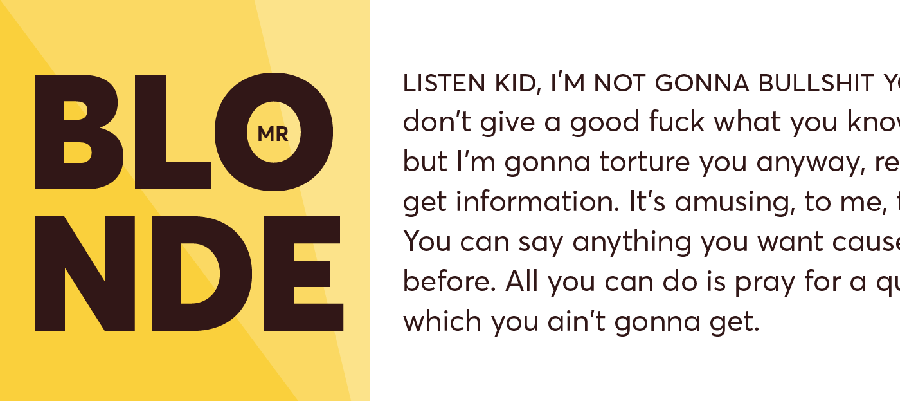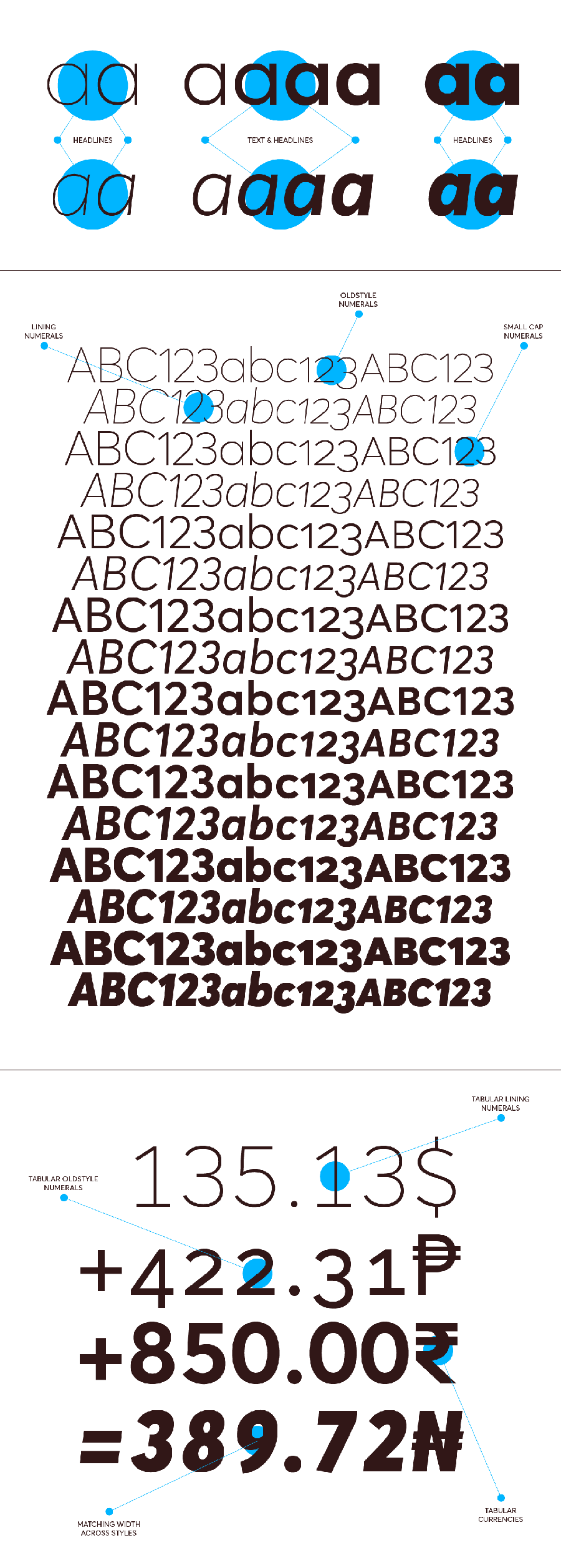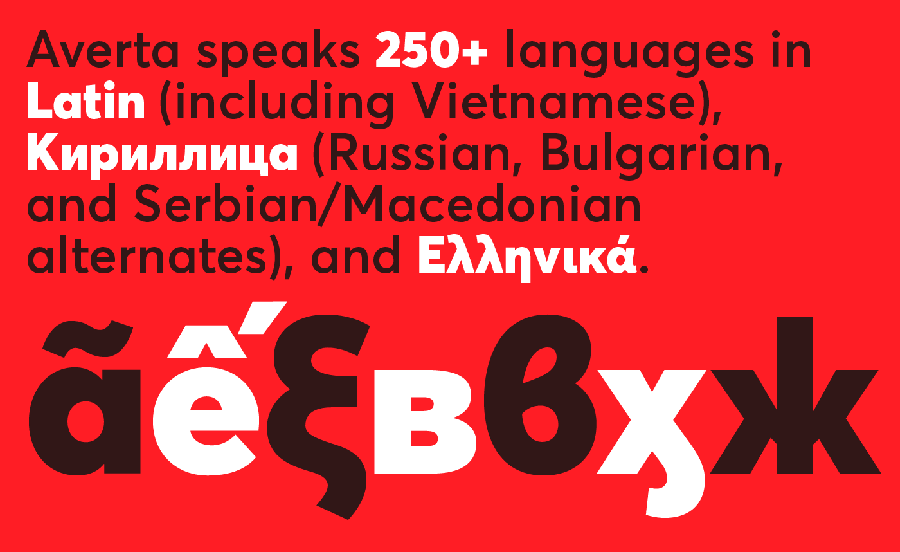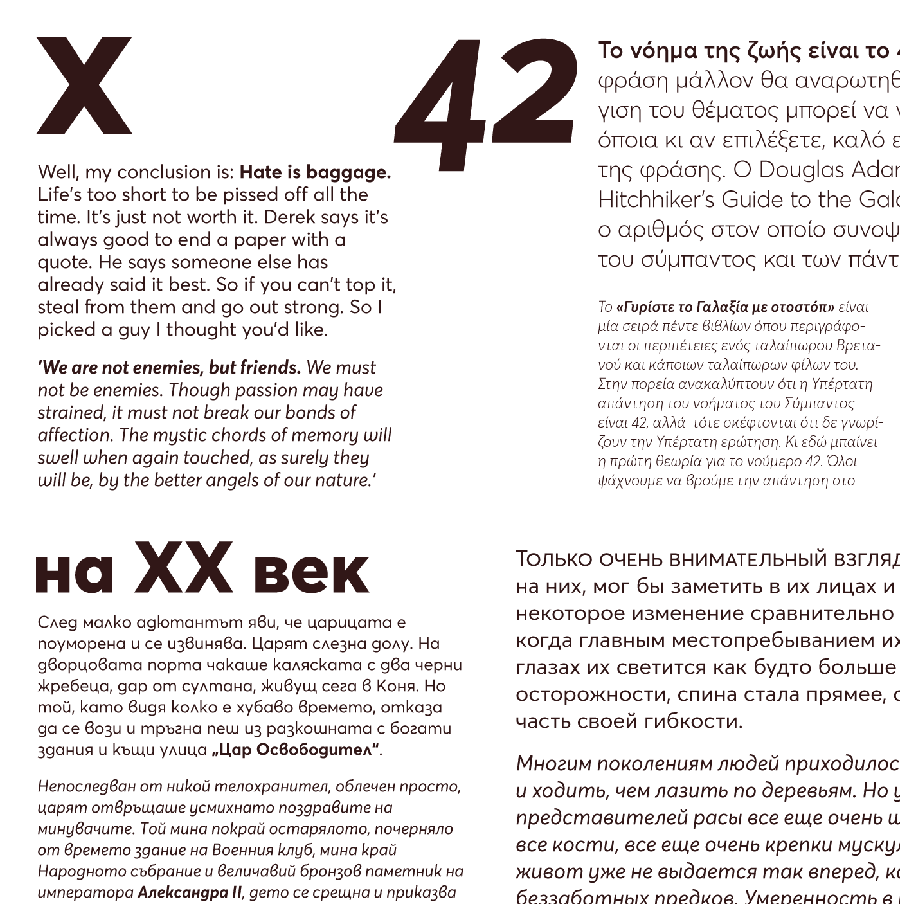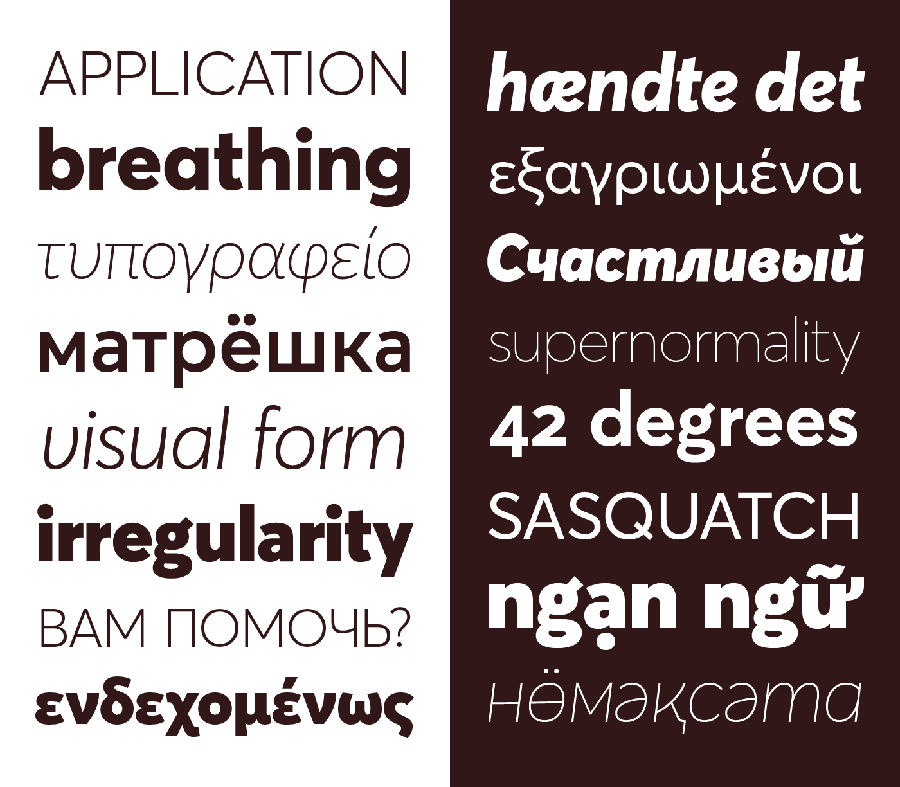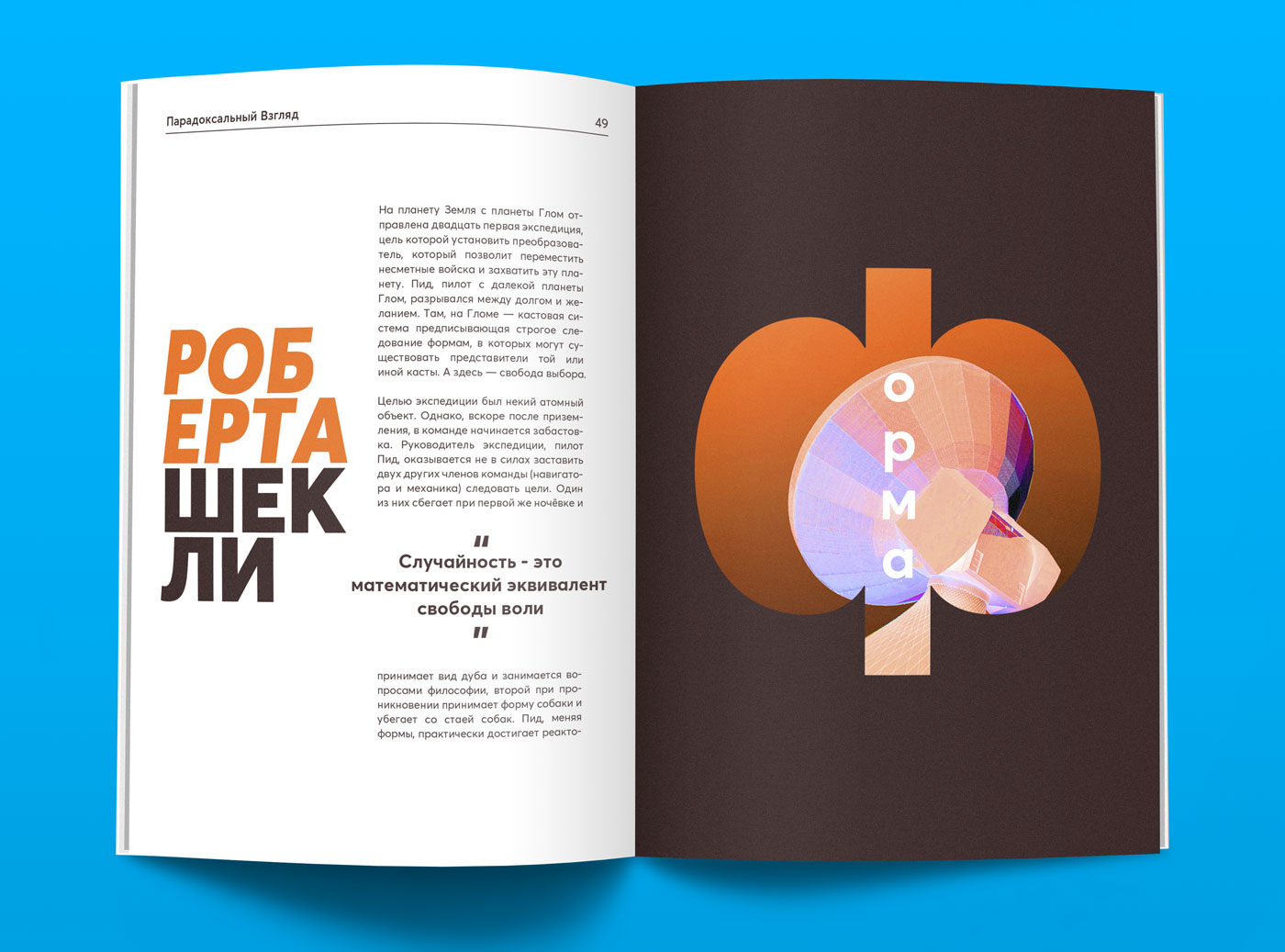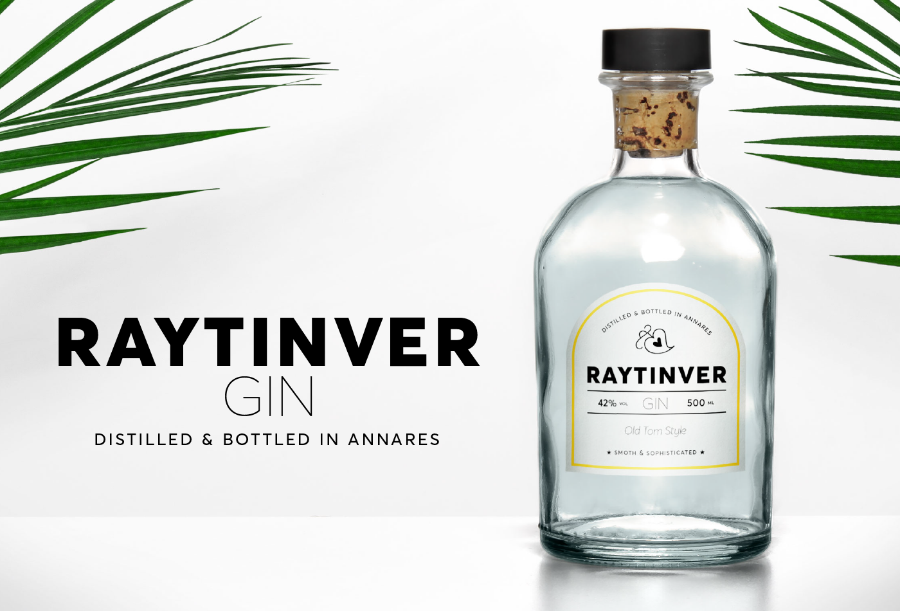
Averta Sans家庭免费演示
Averta Sans家庭免费演示是一个简单,但吸引力,个性的几何无衬线家庭。纯粹的几何圆形,开放的光圈,以及低对比度的笔触设法表达直接的音调。因此,这种字体已经成为一种现代主义,中性和友善的字体。另外,Averta非常适合在各种媒体上使用。中央风格可用于文字大小,而极端间隔更紧密,形成更连贯的标题。真正斜体的活力为整个家庭增添了互补的一面。它提供了额外的多功能性,使得Averta成为从标牌到品牌和编辑设计等各种用途的绝佳工具。